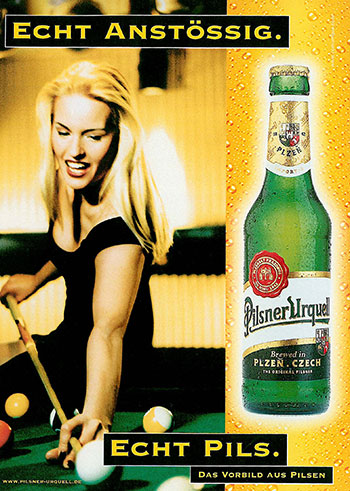
Fontnaepfchen 3: abstoessige HeadlineEcht abstossend die Rechtschreibung von Pilsener Urquell. Warum denken die
Werber nicht nach, bevor sie eine Schrift auswählen? Alles wird getestet:
Geschmack, Zielgruppe, Wettbewerb, Werbemedien ... Aber keiner hat gemerkt, dass
man mit Copperplate nicht deutsch schreiben kann. Und ein ß zwischen
![]() Form follows form: Hier wurde Pilsener Urquell eine Kampagnenschrift
empfohlen, die zwar schön aussehen mag, aber nicht funktioniert bzw. den
Texter unnötig einschränkt. Nach Einführung der neuen
Rechtschreibreform hat sich auch unser Lesen verändert: Aber die Masse der